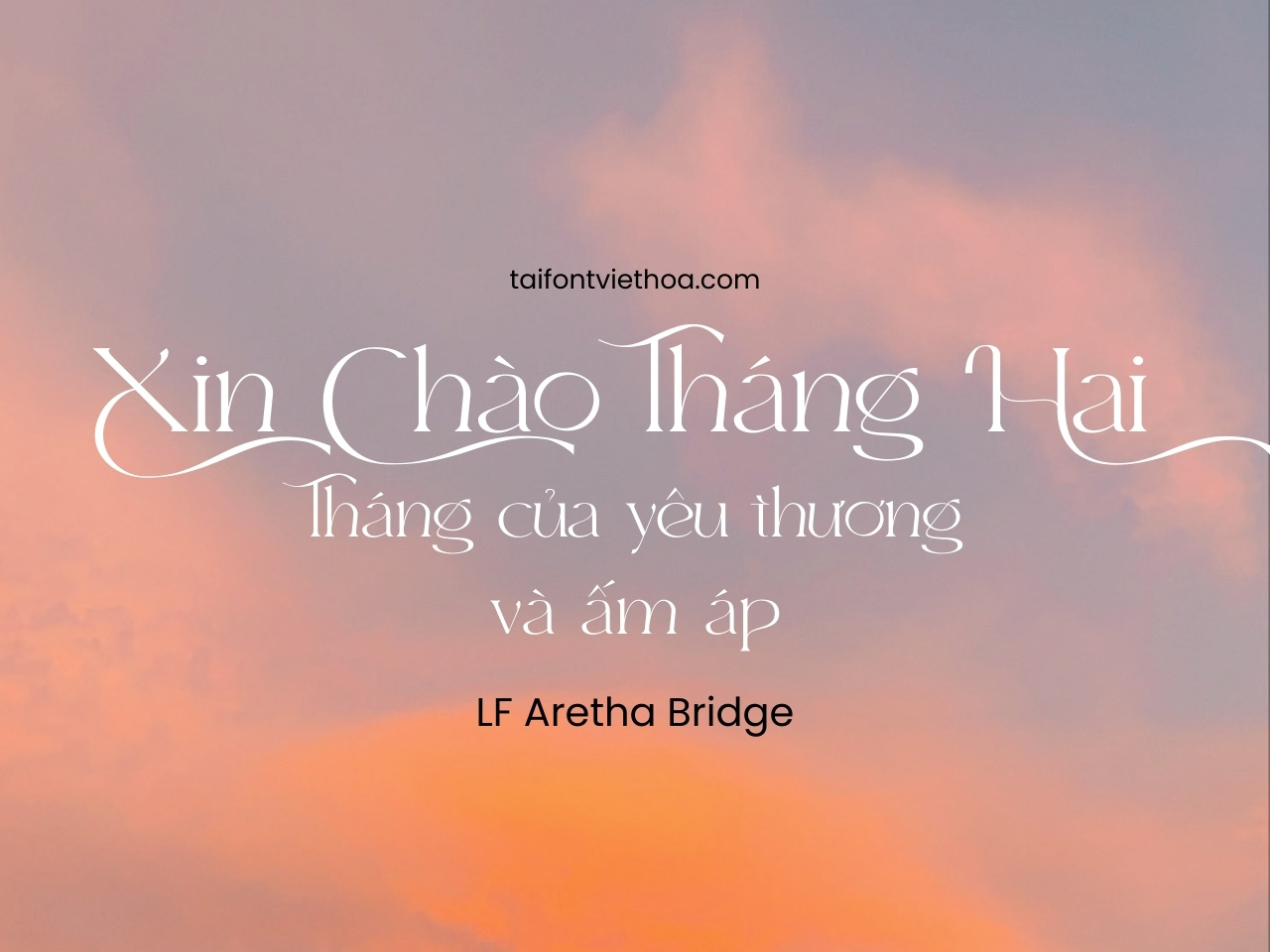
Font việt hóa Lf Aretha Bridge
Tác giả Font: 177Studio
Giới thiệu font Lf Aretha Bridge – Kiểu serif cổ điển từ 177Studio
Lf Aretha Bridge là một font serif mang đậm phong cách cổ điển và nghệ thuật, được phát triển bởi 177Studio – một trong những nhà sáng tạo nổi bật trong giới thiết kế typography hiện đại. Kiểu chữ này mang âm hưởng retro kết hợp đường nét hiện đại, tạo nên sự hòa quyện hoàn hảo giữa thanh lịch và cá tính. Với độ tương phản rõ ràng giữa các nét thanh đậm và phần chân chữ được cách điệu tinh tế, font rất phù hợp với các thiết kế mang tính hoài niệm, sang trọng và đặc biệt. Phiên bản Việt hóa do Lengnef thực hiện, hỗ trợ tiếng Việt và hơn 90 ngôn ngữ khác. Font hiện đã được taifontviethoa.com sưu tầm, chọn lọc và giới thiệu đến cộng đồng thiết kế sáng tạo như một giải pháp typography cho các dự án cần chiều sâu văn hóa và tính thẩm mỹ cao.
Chất hoài cổ tinh tế và ứng dụng của Lf Aretha Bridge
Lf Aretha Bridge nổi bật với kiểu dáng serif dày, độ cong nhẹ nhàng ở một số điểm chữ, tạo cảm giác cổ kính nhưng không hề lỗi thời. Cấu trúc chữ chắc chắn, tính trình bày tốt giúp font dễ dàng áp dụng vào các thiết kế như tiêu đề sách nghệ thuật, tạp chí cao cấp, poster sự kiện văn hóa, nhận diện thương hiệu thủ công, hay bao bì sản phẩm truyền thống. Font lý tưởng cho các ngành như giáo dục, công nghệ mang yếu tố bản địa, bất động sản cao cấp, quảng cáo truyền thống và các chiến dịch văn hóa. Các dịp sử dụng phù hợp gồm Trung thu, Halloween, lễ hội, sinh nhật thương hiệu hoặc các sự kiện cần chiều sâu lịch sử và tính thẩm mỹ tinh tế.